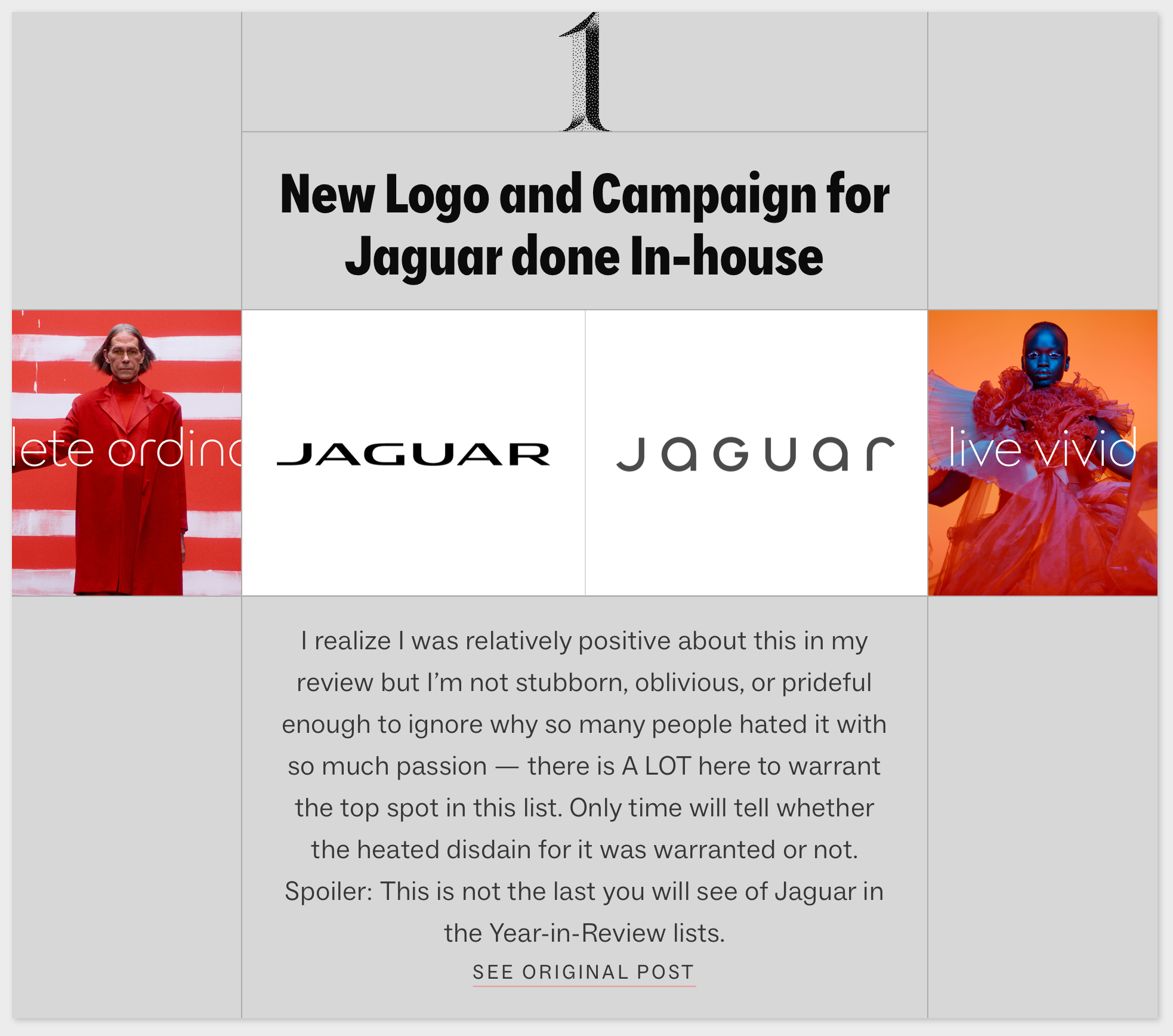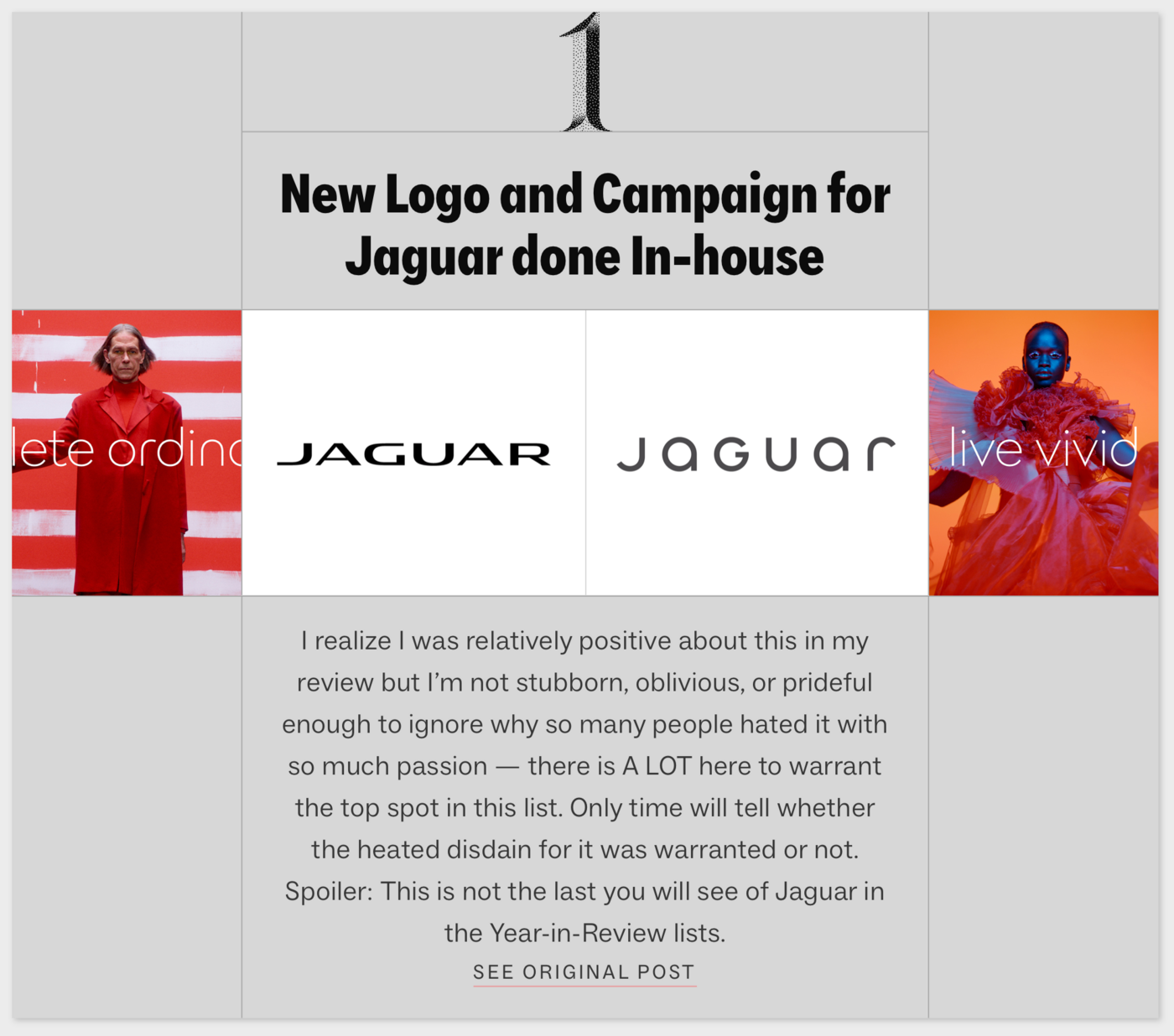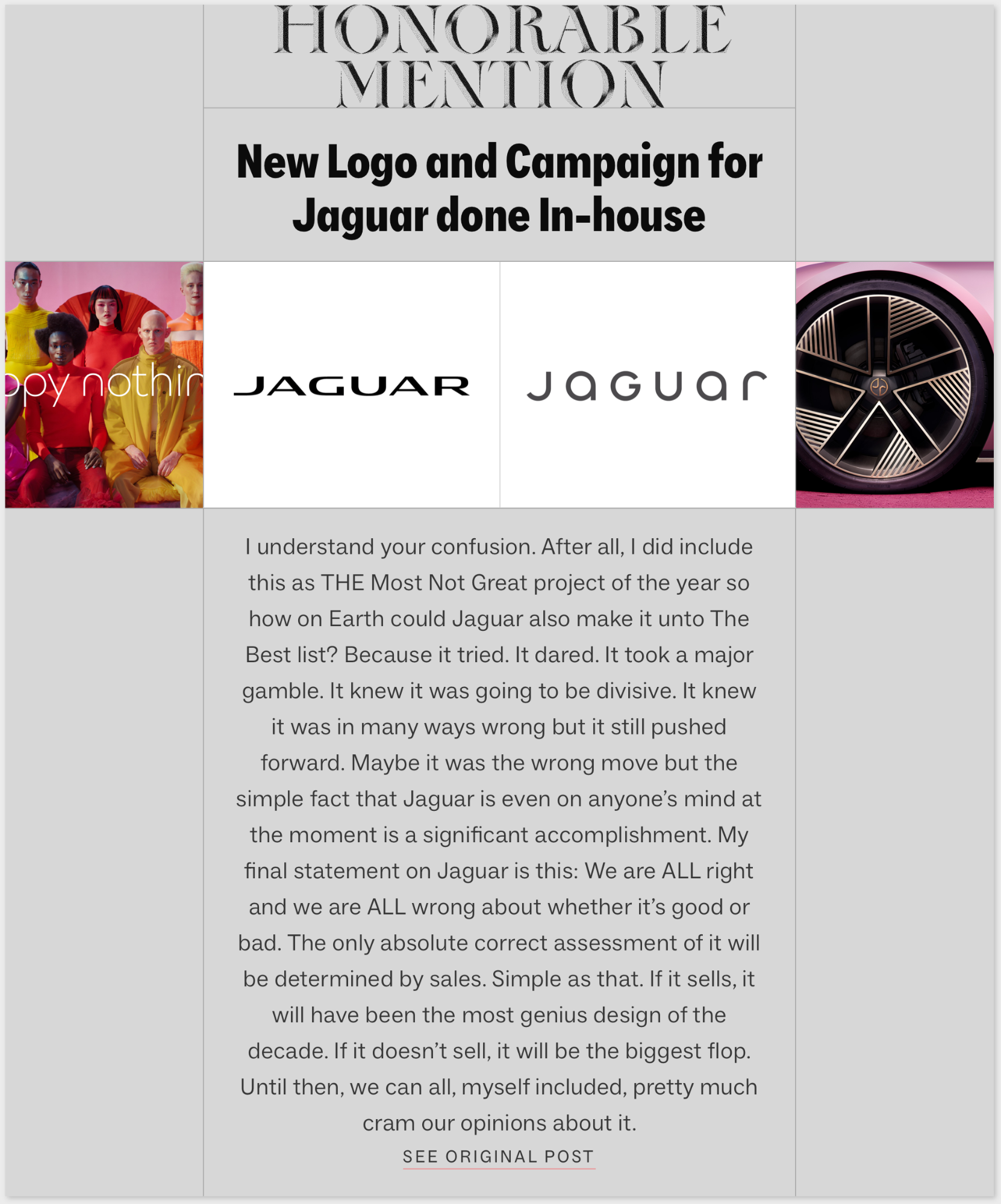
Vielleicht lohnt es sich ja mal einen Thread zu diesem Thema zu starten. Hier könnten wir Anwendungsfälle besprechen, die uns irgendwie beschäftigen. Vielleicht weil sie skurriler Natur sind, wunderbar ausgeklügelt, unverschämt teuer oder günstig, oder, oder, oder …
Auslöser dafür ist bei mir ein Blick auf die Tesla-Webseite um mal das neue autonome Fahrzeug unter die Lupe zu nehmen. Da fällt mir auf, dass es keine Gotham mehr zu sehen gibt sondern die Universal Sans. Das finde ich unter zwei Aspekten bemerkenswert: Erstens der Fontname, der ziemlich gut Elon Musks Programmatik auch außerhalb dieses Planeten Leben zu ermöglichen beschreibt. Und zweitens dieser Font selbst, der technologisch schon recht früh aufgezeigt hat, was in Sachen Variabilität und rechnergestütztem Fontdesign so möglich ist. Das scheint mir eine außergewöhnlich bewusst getroffene und zielgerichtete Wahl zu sein. Was denkt ihr?
Das scheint mir eine außergewöhnlich bewusst getroffene und zielgerichtete Wahl zu sein.
Das lässt sich natürlich alles (im Nachgang) hinein interpretieren – aber einen klaren Anhaltspunkt für diese Annahme gibt es meines Erachtens nicht. Vielleicht gibt es auch ganz profane Gründe für die Wahl der Universal Sans.
Ist das so? Die Schrift ist vier Jahre alt (2020), und so weit ich mich erinnern kann, kamen die ganzen Features erst nach und nach dazu. Zu Beginn war das doch nur eine sachliche Sans mit ein paar Glyphenvarianten – erst später kam die Ausbaustufe dazu, inklusive Landing Page und Möglichkeiten der Individualisierung.
Von all den Möglichkeiten, die theoretisch in der Schrift stecken, macht die Tesla-Seite auch kein Gebrauch (oder übersehe ich da irgendwas?). Im Gegenteil: ich finde den Einsatz der Schrift auf der Website leider maximal uninspiriert. :-|
Danke fürs Teilen Deiner Perspektive! Ich hätte es Tesla zumindest auch nicht zugetraut so genau hinzuschauen bei der Fontsuche und -auswahl, wenn denn meine Interpretation überhaupt zutreffen sollte.
Echt? Ich meine da ging schon viel von Anfang an. Ich kenne sie aber auch nur über diese Webseite und kann mich noch über Diskussionen erinnern, wie weit »automatisierte« Fontgestaltung schon fortgeschritten ist.
Gut, das muss ja auch nicht sein. Aber wenn sie damit »Technologieführerschaft« illustrieren wollten, wäre das natürlich folgerichtig.
Ja, das sehe ich auch so. Ich finde sie zunächst einmal recht klein eingesetzt im Vergleich zur Gotham.
Ich finde es schlimm bis furchtbar. Aber ich mag auch die aktuellen Jaguars nicht und bin nicht Zielgruppe ... Die Personen in der Anzeige sehen für mich auch nicht so aus als würden sie einen Jaguar oder überhaupt ein Auto fahren.
Getoppt wird das nur noch durch das Redesign der Friedrich-Ebert-Stiftung. Das die eigens gestaltete Hausschrift weder Kyrillisch noch Griechisch unterstützt ist in Anbetracht der Büros die die Stiftung weltweit unterhält schon sehr fragwürdig ...
Mein erster Gedanke war auch eher »Benetton« …
Interessanter Punkt, soweit habe ich noch gar nicht gedacht. Ich war gleich bei Fashion.
Und die Schrift als solches? Durch die fehlenden Sporne und gleichbleibende Linienstärke habe ich zum Beispiel beim r in Lesegrößen immer das Gefühl da bricht was weg im Knick. Müsste man da mehr ausgleichen?
Ich mag den neuen Schriftzug, er hat was! Allerdings bringe ich ihn auch überhaupt nicht mit Jaguar und seiner bisherigen Markenidentität zusammen. Der Schriftzug weckt bei mir direkt Assoziationen zu Skandi- oder Japandi-Designs. Mode oder Möbel. Oder ein zumindest ein futuristisches Flugauto. Ob Jaguar da wohl hin will? :-?
Jaguar muss da hin. Beziehungsweise muss Jaguar erst mal weg vom Image der dauerkaputten englischen Autos mit Technik aus den 60er-Jahren. Da sie Verbrenner komplett einstellen und sogar ein Jahr lang keine Neufahrzeuge verkaufen wollen oder werden, seh ich das als kompletten Restart. Der Jaguar flog aus dem Logo, die Hausschrift ist genauso beliebig wie BYD und Konsorten. Kommt scheinbar an beim Publikum, meint zumindest die indische Mutterfirma. Die wenigen zahlungskräftigen Verbrennerfahrer, die Jaguar hat(te), gehen auf die 100 zu …
Oh, und noch etwas fällt mir ein: Europa ist nicht mehr Zielgruppe in der Automobilindustrie (gesättigte Märkte, systemisch zerstörte Binnennachfrage, jahrzehntelanges Missmanagement (mal ehrlich, Volkswagen steckt in der Krise? Die haben mal den Bericht "Grenzen des Wachstums" finanziert in den 70ern -- hätten sie auch mal lesen können), Innovationsfeindlichkeit, ...). Umsatz wird Asien gemacht, daher sind "unsere Augen" irrelevant. Ja, mir fehlt die Tiersymbolik. Aber vielleicht ist diese in beispielsweise China negativ belegt?